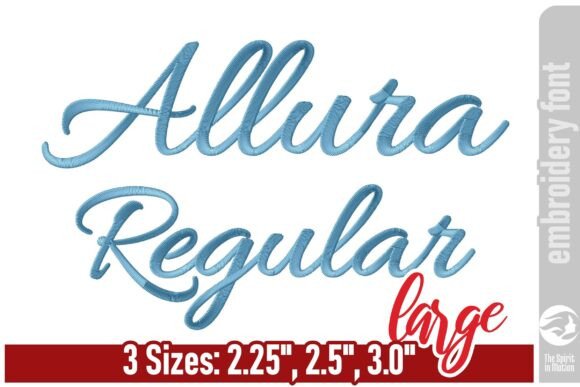
Allura Script Embroidery Font - Large
หากคุณกำลังมองหาเนื้อหาคุณภาพสูงเช่น Allura Script Embroidery Font - Large แพ็คเกจพรีเมียมนี้เป็นตัวเลือกที่ยอดเยี่ยมสำหรับโปรเจ็กต์สร้างสรรค์ของคุณ
สร้างขึ้นอย่างแม่นยำ Allura Script Embroidery Font - Large ให้เวกเตอร์ที่สะอาด พิมพ์ตัวอักษรที่ราบรื่น และใบอนุญาตเชิงพาณิชย์เพื่อความสบายใจ